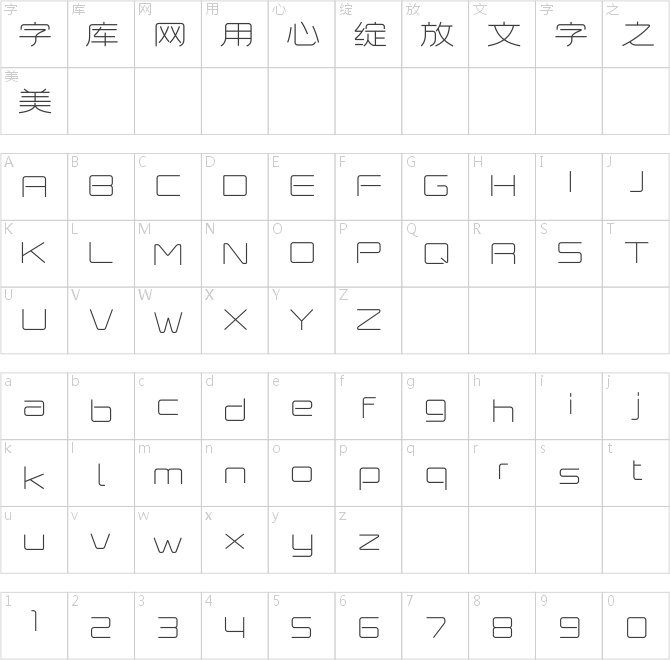
字體名稱: 方正秋刀魚潤黑
方正秋刀魚潤黑
作者秋刀魚,本名姜鵬飛,這款字體的靈感來自于一首古詩《相思》,意在表現一種傳統委婉的情感,作者早些年做過一篇字體設計帖子,以文字與海報的形式結合,去體現傳統之美。后來經過不斷嘗試與優化,最終確定將它做成一套完整的字庫,其字為黑體大形,結構寬扁,重心平穩,筆畫纖細溫潤,給人典雅平和的感覺,故取名潤黑體,一些筆畫的設計參考隸書的感覺,整體有傳統古樸的韻味。